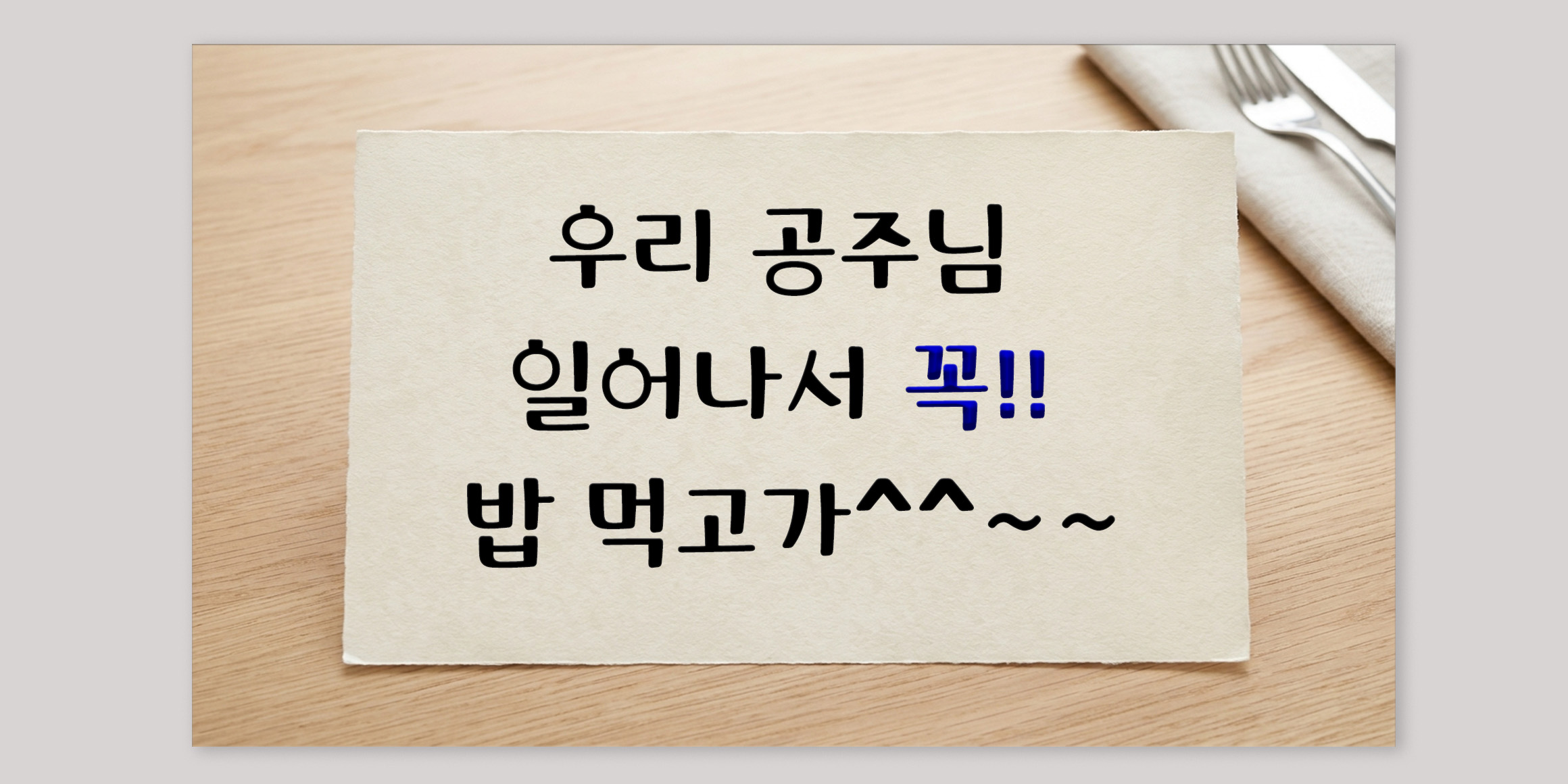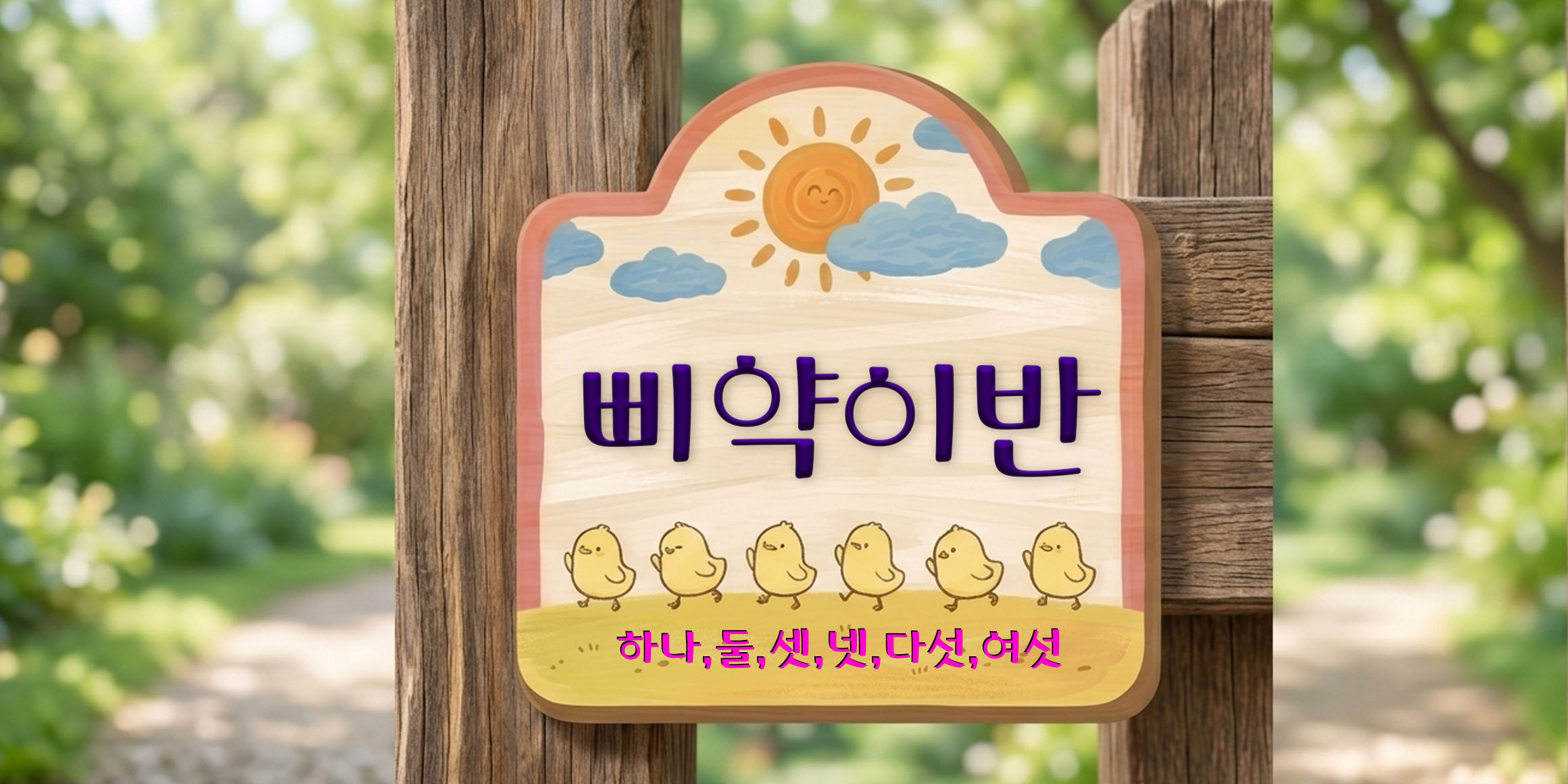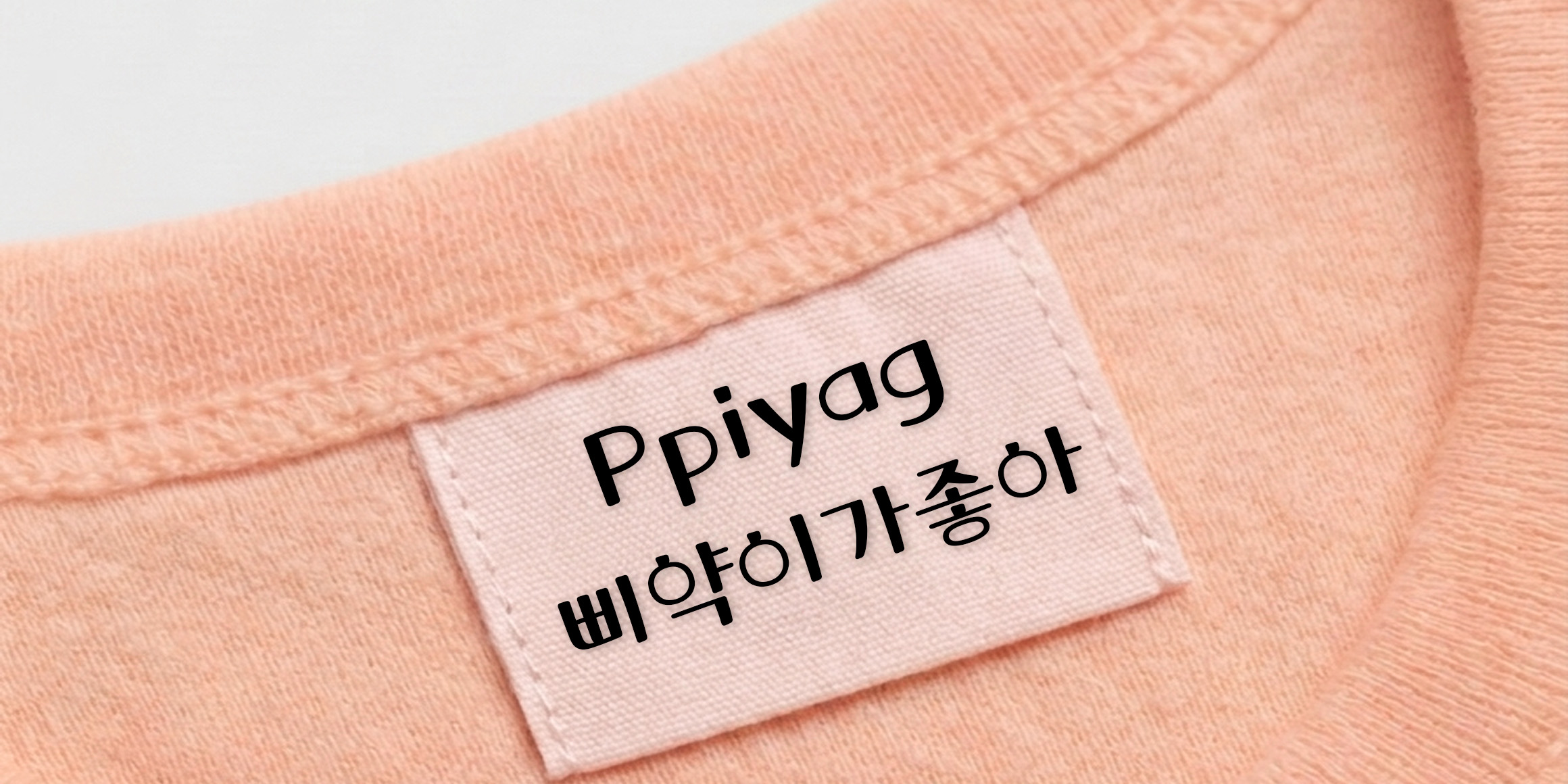
자소의 뼈대가 반듯하면서도 모서리가 둥글게 처리되어, 단정함과 귀여움이 공존한다.
글자의 중심선이 중앙에 머물러 있어, 마치 아기 병아리가 아장아장 균형을 잡으며 걸어가는 듯한 리듬감을 준다.
모서리 부분을 라운드 처리하여 더욱 부드럽고 편안한 느낌을 갖는다.
유아동 및 교육 콘텐츠: 어린이집, 유치원 알림장, 초등학생 교재 타이틀, 동화책 자막
친근한 브랜드 마케팅: 캐릭터 굿즈 패키지 design, 반려동물 용품 브랜드의 로고나 상세페이지 제목
SNS 및 영상 자막: 일상 브이로그(Vlog), 육아 일기 릴스/쇼츠의 포인트 자막
문화 및 여가: 베이커리나 디저트 카페의 귀여운 메뉴판 구성등에 사용을 권장한다.